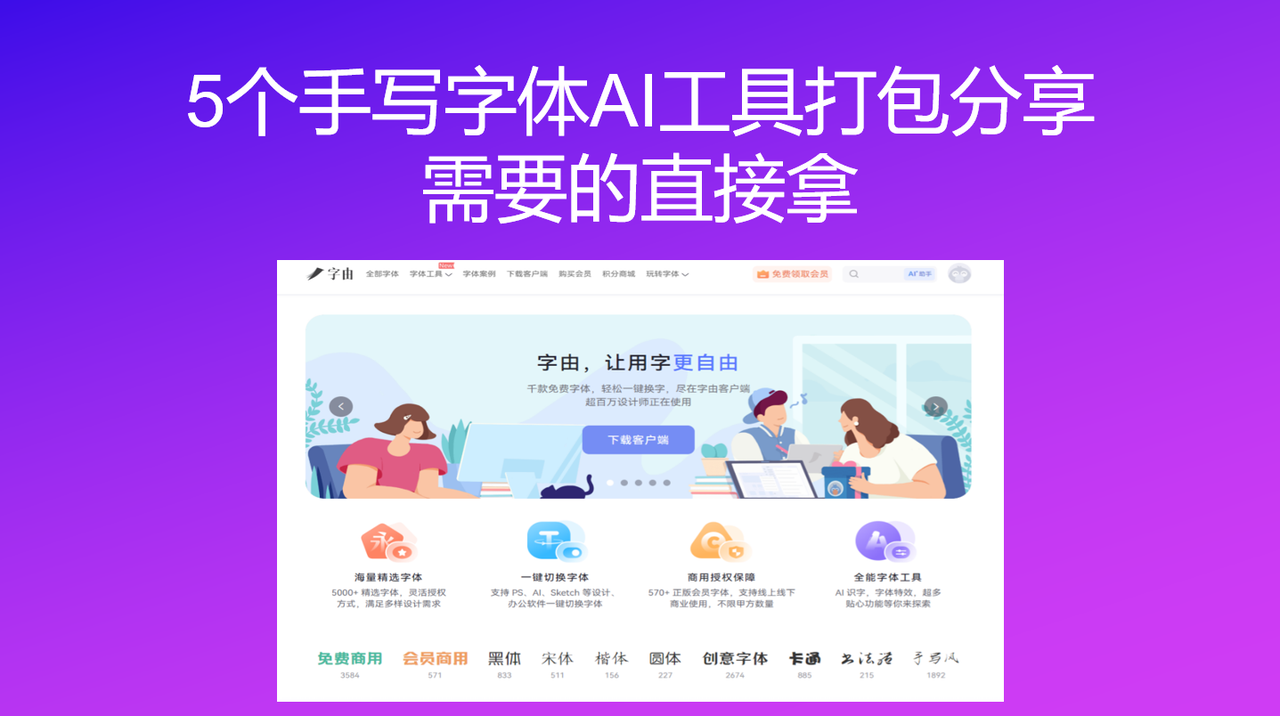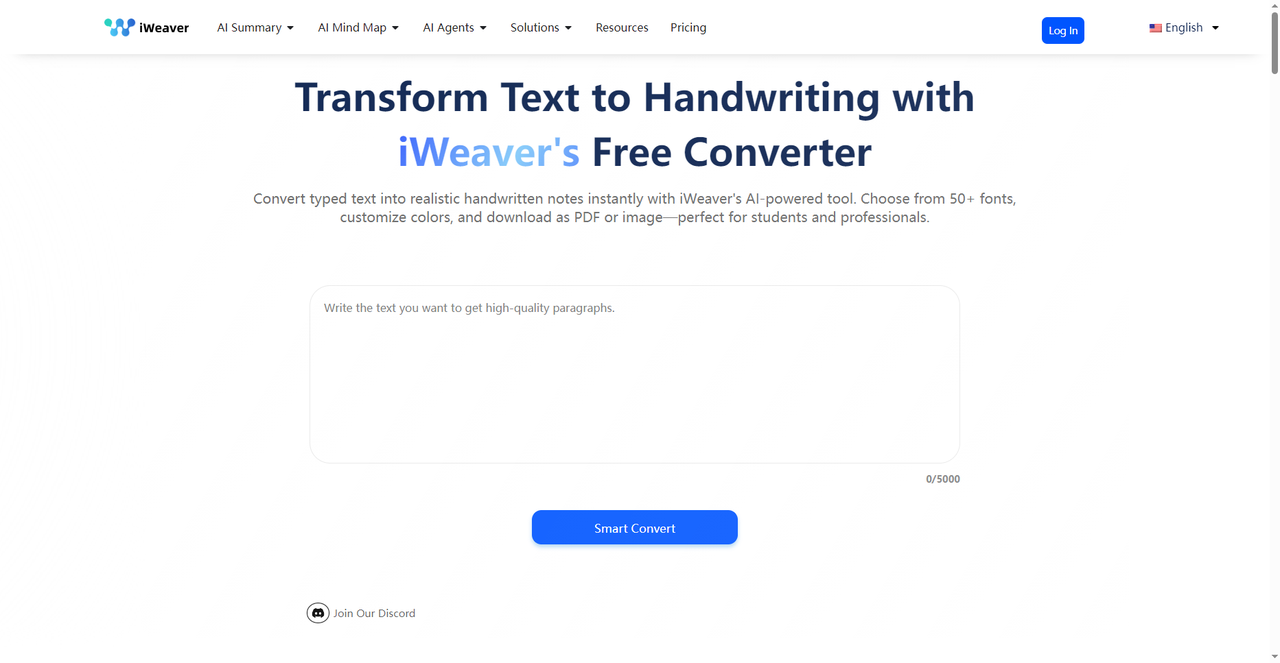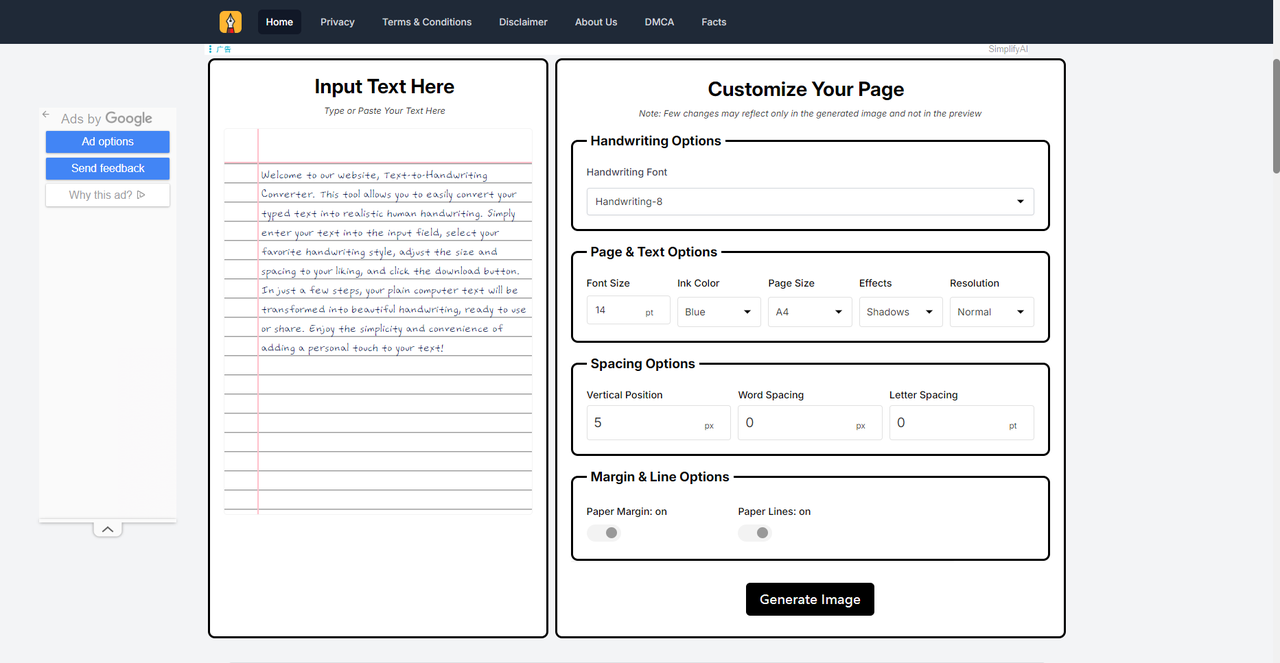
5个手写字体AI工具打包分享,需要的直接拿
手写体放在十年前还算是我们能经常接触到的东西,但是现在却好像变得没那么重要了。因为现在几乎人手一台电脑或者是一部手机,想要传达信息,可以直接说话发语音、打电话甚至是语音转文字即可,打字越来越快,提笔写字的机会却越来越少。但有些场景,偏偏需要手写的感觉,比如说想要给朋友写信,给学生判作业,又或者是给视频加一个手写标题,单纯怀念那种有温度的文字。好在现在AI 的发展之快以至于有了手写字体AI 工具,能帮你把打好的字,一键变成逼真的手写体。今天我就筛选了 5 个亲测可用的手写字体AI 工具,需要的记得收藏。
我第一个要推荐的手写字体 AI 工具是字由,虽然字由主打的是字体库,但是AI 相关的工具它也一个都没落下。
你不需要会书法,也不需要装字体,输入文字,选个模板,几十秒就能生成一张手写感的艺术字。关于怎么使用字由的AI字体工具,下面我会用很简单的步骤教会你:
- 进入AI字体页面后,在搜索框里输入“手写”“书法”“毛笔”“小楷”“行书”等关键词,系统会自动筛选出所有带手写质感的模板。你也可以直接点进“国潮风”“文艺风”等分类里慢慢翻,很多模板本身就是手写风格。
- 点击选中的模板,进入编辑页面。在输入框里填你想生成的文字(比如“春日来信”“手写时光”“见字如面”)。注意:最好和模板的字数保持一致,模板是四个字,你就填四个字;模板是两个字,你就填两个字,这样生成的效果最自然。如果字数不一致,AI也会尽量适配,但可能会有些偏差。
- 确认文案后,点“立即生成”,等20-30秒左右,系统就会输出设计好的手写艺术字图片。生成后可以预览效果,不满意就换其他模板再试,或者微调文案重新生成。不要忘了每天可以免费领取算力点,这样可以免费生成手写体文字。
这些模板都不是单纯的字体,而是带笔触、带墨韵、带纸张纹理的完整设计。你选好模板,换成自己的文案,生成的就是一张可以直接用的图。这要比自己去设计省时省力得多。
AI字体生成的效果已经能满足大部分需求,但如果你想要更自由的控制,比如想自己排版、自己调颜色、自己加背景,字由的传统字体库也能帮忙。打开“全部字体”,在左侧“字体类型”里点“手写体”或“书法体”,就能看到大量手写风格的字体。
2、iWeaver
iWeaver 是一个AI驱动的手写字体AI 生成工具,可以把打好的文字转换成逼真的手写笔记。从它的首页标语就可以很直接地看出来了。这个网站的核心功能包括:
- 支持50多种手写字体风格
- 可以自定义颜色
而且这个网站提供了几种预设风格:“Student Notebook”(学生笔记本风格)、“Casual Writing”(自然放松的书写)、“Neat Layout”(整洁布局)、“Letter Style”(优雅专业手写)。无论你是学生做笔记,还是专业人士需要手写文档,都能找到合适的风格。并且操作也十分简单,可以直接输入你想要生成的文字,点击“Smart Convert”,等待几秒钟就能生成。生成的效果很逼真,纸张纹理、墨迹深浅都有模拟,几乎看不出是电脑生成的。
3、Text-to-Handwriting
Text-to-Handwriting 是一个功能更丰富的手写生成工具,提供了大量可调节参数,让你能精细控制生成效果。具体的调整细节有:
- 手写字体:可以从多种手写风格中选择(如Handwriting-8)
- 字体大小:从14pt起可调
- 墨水颜色:蓝色、黑色等可选
- 页面尺寸:A4等标准尺寸
- 效果:可添加阴影
- 分辨率:普通、高清可选
- 间距:垂直位置、字间距、字母间距都可调
- 页边距:开关控制
- 纸张线条:开关控制
这样精细调节的好处就是你可以生成完全符合自己需求的手写效果。比如想模仿真正的作业本,可以打开纸张线条;想做一封复古风格的信,可以调成泛黄的颜色加阴影。调节好后点击“Generate Image”,就能下载生成的手写图片。
4、AI Text to Handwriting
这个网站相比较前面的两个网站它的特点是支持多种输出分辨率和画幅比例,生成的图片质量很高。核心功能有以下几项:
- 输入文字:支持多行文字输入,有示例“Dear friend, It was wonderful to see you the other day...”
- 手写风格:可以选择“Neat Cursive”(整洁草书)等多种风格
- 画幅比例:支持21:9、16:9、3:2、4:3、2:3、9:6等多种比例
- 分辨率:支持1K(常规)、2K(高清)、4K(超清)输出
主要风格是正式流畅的草书,非常适合邀请函或信件,正式流畅的草书,非常适合邀请函或信件
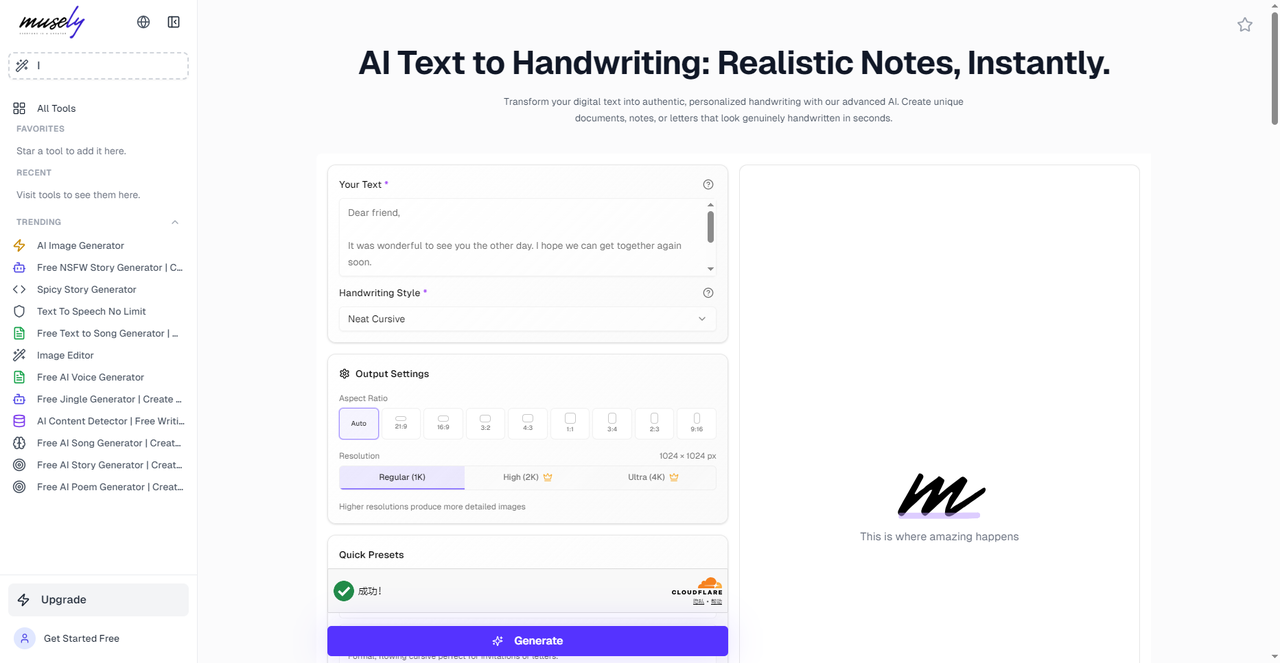
5、多功能手写生成器
最后一个工具功能更强大,不仅支持自带的手写字体,还允许用户上传自定义字体。如果你对自带的字体不满意,或者有自己的手写字体文件,上传后就能生成专属手写效果。这个功能对追求个性化的用户特别友好。
以上推荐的这五个手写字体AI 工具主要是代表了两种不同的手写路径,后面四款工具都是把文字“生成”手写图片,适合做笔记、信件、作业等场景;而字由则是提供现成的手写风格字体,直接在设计软件里调用,适合做封面、海报、标题等需要排版的设计场景。但是一般情况下都是需要手写风格的字体来做设计,那么我会推荐你选择字由,3000+字体随便你挑选,总有一款适合你。